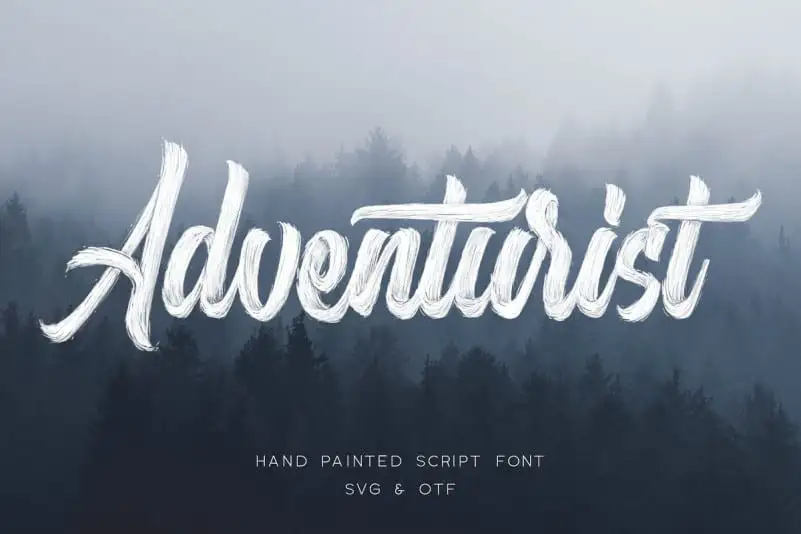
A Adventurist Script Font é uma escolha perfeita para aqueles que buscam uma fonte que reflete a essência forte e natural do estilo hand-drawn. Este é um tipo de letra bold, cuidadosamente elaborado, ideal para aplicar em designs inspiradores. Com curvas atraentes e uma linha urbana inovadora, a Adventurist Script combina um aspecto fresco e urbano com um toque de elegância natural. Sujeito à criatividade do designer de fontes Surplus Type Co., esta fonte vem em duas versões: o formato .otf (regular) e uma SVG mais detalhada. A opção entre essas duas versões torna-se especialmente útil para criar soluções gráficas inspiradoras. Para quem busca um visual atraente que não apenas destaca, mas também reflete os interesses urbanos contemporâneos, Adventurist Script é sem dúvida uma excelente escolha. A Adventurist Script atinge exatamente o ponto ideal entre rusticidade e sofisticação, garantindo tanto um toque moderno quanto um ar de profundidade que se destaca em qualquer projeto. Não importa se você está trabalhando em criações para o mundo digital ou impressão – a Adventurist Script oferece o suporte necessário para alcançar os seus objetivos criativos.